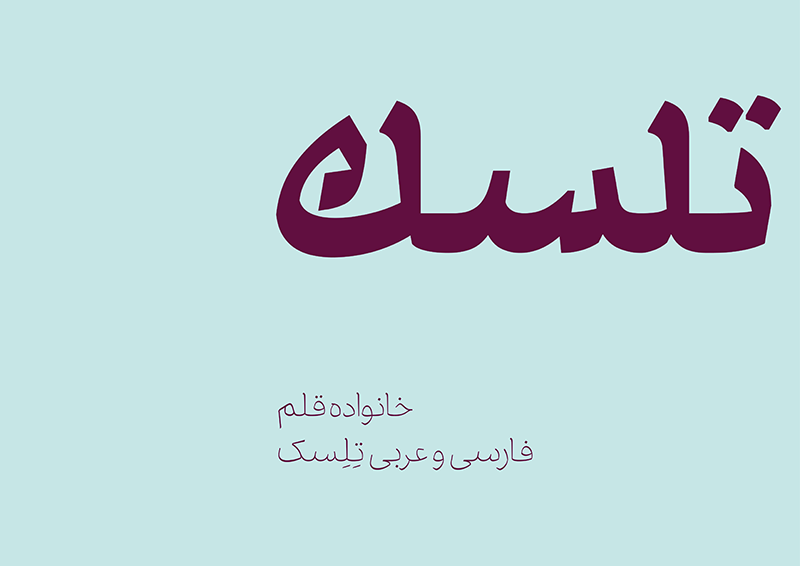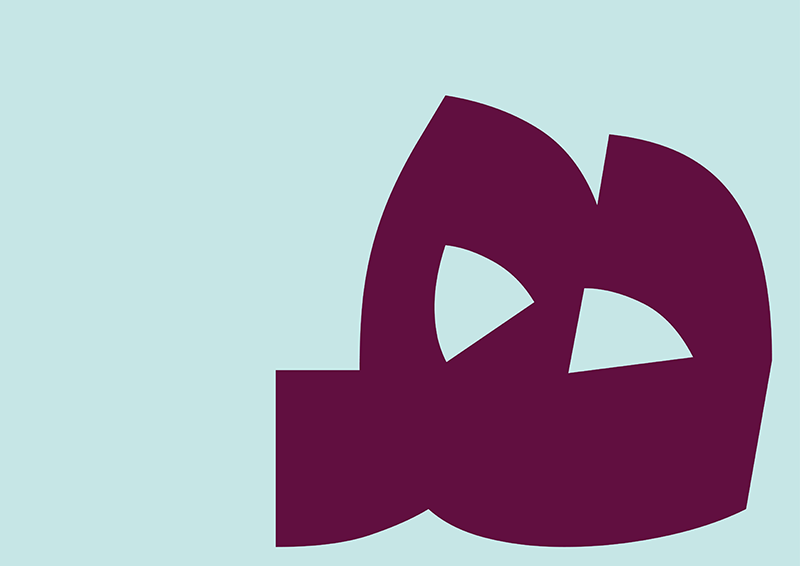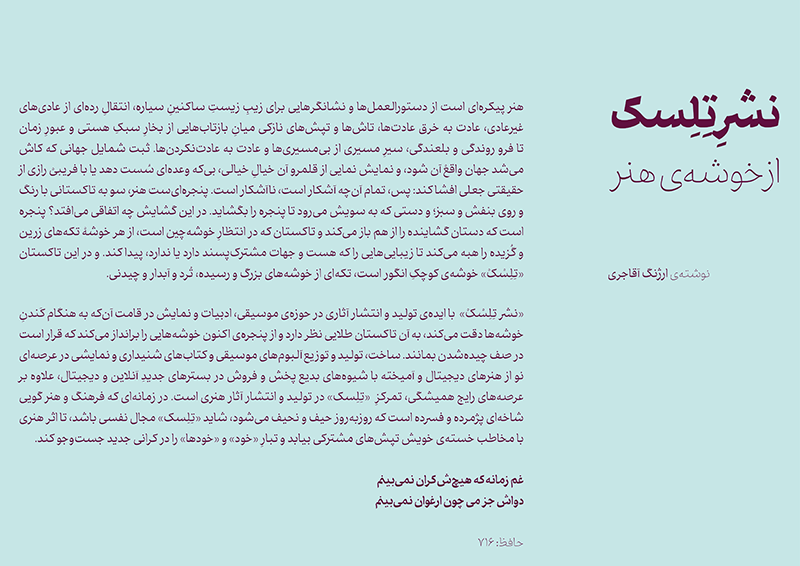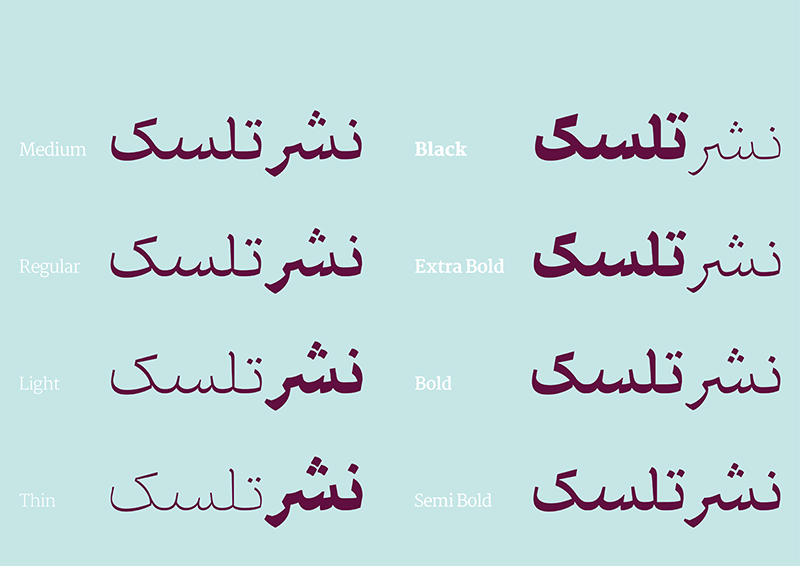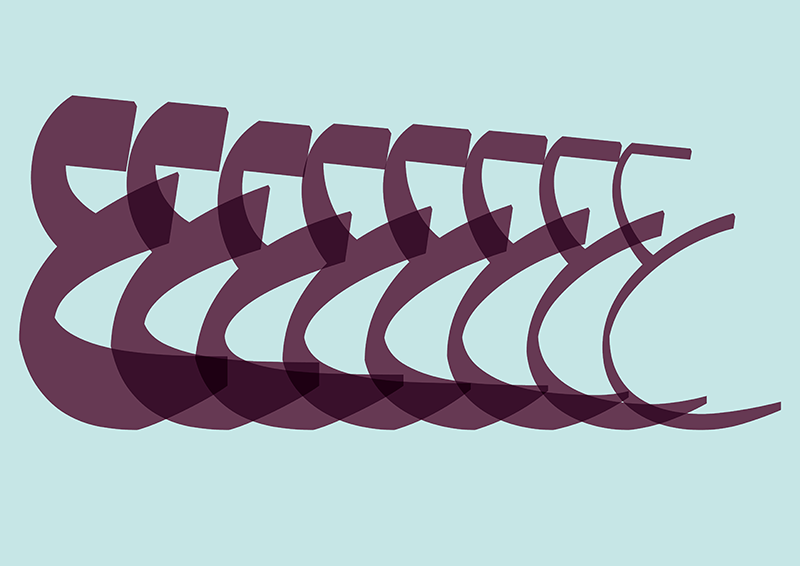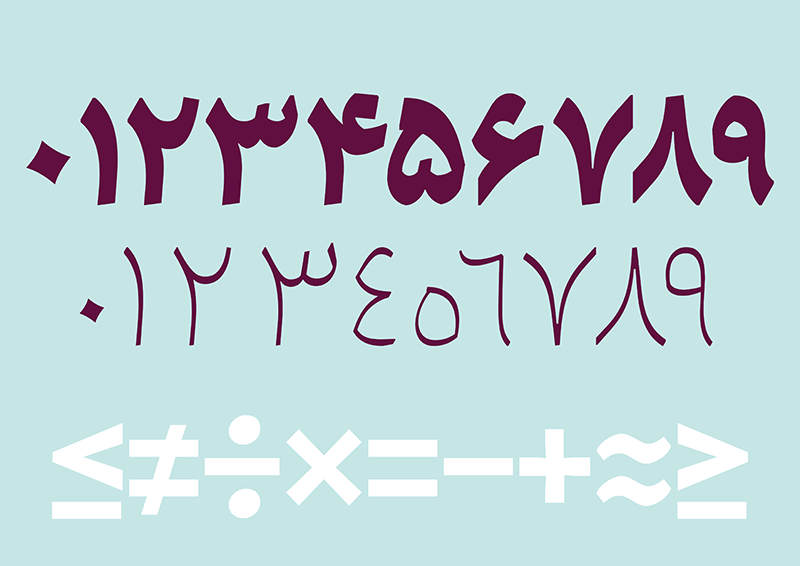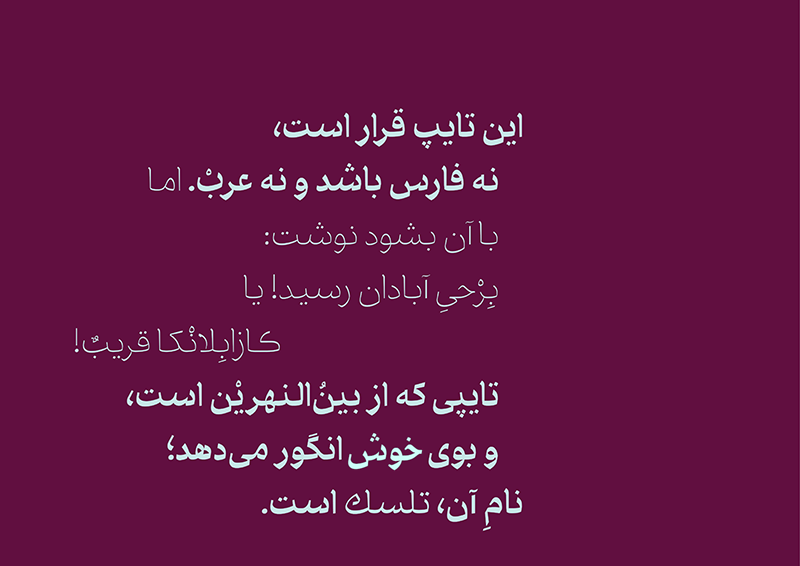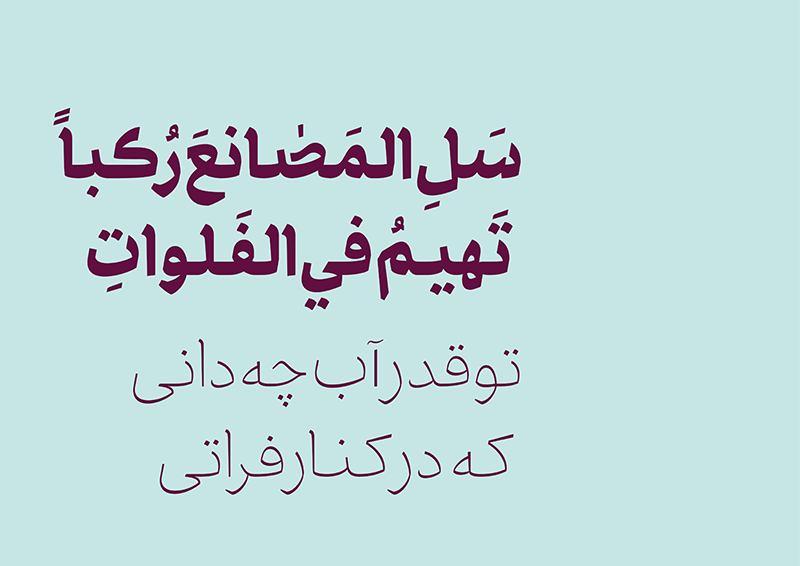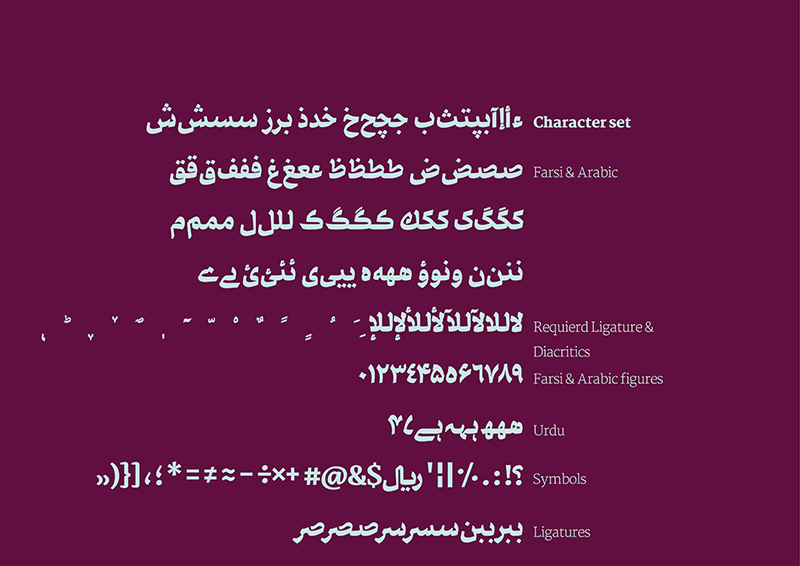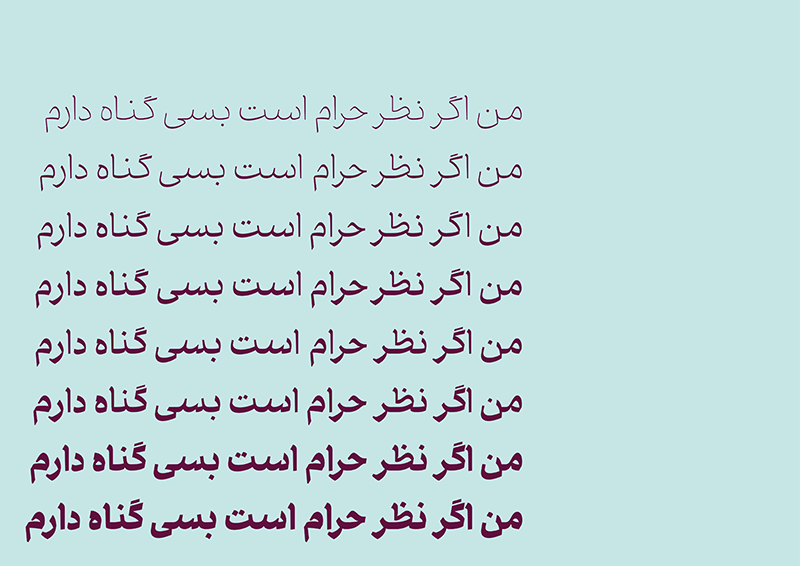
قلم تلسک font Tlesk
قلم تلسک
کاری از امیر مهدی مصلحی
درباره قلم تلسک
سال۱۳۹۶، مدیر نشر موسیقی تلسک، ارژنگ آقاجری، به استودیو مرکزی سفارش دیزاین هویت دیداری آلبوم‌های موسیقی‌اش را داد. از آنجایی که مشی دیزاین ما در استودیو مرکزی، پیروی از منطق ساده‌گرایی در دیزاین بود، بر آن شدم که با ساخت قلمی برای نوشتن عناوین آلبوم‌ها به رسیدن به راه‌حل دیزاین نزدیک‌تر شوم. بعد از شنیدن موسیقی اولین آلبوم نشر تلسک، «طاق‌های ضربی بغداد» که زخمه‌های قانون در آن چون درخشش آب‌های فرات در برق آفتاب جنوب بود، فرم‌هایی پدیدار شد که طعم و بوی آن سرزمین‌ها را داشت. افزون بر آن، موسیقی‌های نشر تلسک غالباً معاصراند؛ بنابراین ویژگی مدرن بودن در فرم‌های قلم تلسک نیز ناگزیر می‌آمد. بعد از تولید نسخه اولیه قلم تلسک به شیوه نمایشی و در وزن سیاه، در طی جلساتی با نرم‌افزاری محترم مریم، قرار بر انتشار این قلم، توسط این نهاد متخصص و باسابقه شد.
در طراحی قلم تلسک سعی شده‌است طعمی از خط رقعه، که خط مرسوم نوشتاری جهان عرب است، در آن باشد. تقطیع‌ها و شکست‌های عریان آن، به‌خصوص در حرف «س»، به تنه نخل شبیه‌است. قلم تلسک در اصل برای نوشتن عناوین تدوین شده‌بود اما به تدریج وزن‌های مناسب برای متن کتاب نیز ضروری ‌شد؛ به همین جهت خانواده قلم تلسک از چهار وزن سیاه نمایشی و چهار وزن خاکستری متن شکل گرفته‌است. متفاوت ‌بودن فرم‌ها توأم با جسارت از دیگر اهداف در دیزاین تلسک بوده‌است. ناشر محترم، ارژنگ آقاجری، در توصیف نشر تلسک اینگونه نوشته‌است:
«هنر پیکره‌ای است از دستورالعمل‌ها و نشانگر‌‌هایی برای زیبِ زیستِ ساکنینِ سیاره، انتقالِ رده‌ای از عادی‌های غیرعادی، عادت به خرق عادت‌ها، تاش‌ها و تپش‌های نازکی میانِ بازتاب‌هایی از بخارِ سبکِ هستی و عبورِ زمان تا فرو روندگی و بلعندگی، سیرِ مسیری از بی‌مسیری‌ها و عادت به عادت‌نکردن‌ها. ثبت شمایل جهانی که کاش می‌شد جهان واقعْ آن شود، و نمایش نمایی از قلمرو آن خیالِ خیالی، بی‌که وعده‌ای سُست دهد یا با فریبیْ رازی از حقیقتی جعلی افشا کند: پس، تمام آن‌چه آشکار است، ناآشکار است. پنجره‌ای‌‌ست هنر، سو به تاکستانی با رنگ‌ و روی بنفش‌ و سبز؛ و دستی که به سویش می‌رود تا پنجره را بگشاید. در این گشایش چه اتفاقی می‌افتد؟ پنجره است که دستان گشاینده را از هم باز می‌کند و تاکستان که در انتظارِ خوشه‌چین است، از هر خوشهْ تکه‌‌های زرین و گُزیده را هبه می‌کند تا زیبایی‌هایی را که هست و جهات مشترک‌پسند دارد یا ندارد، پیدا کند. و در این تاکستان «تِلِسْکْ» خوشه‌ی کوچکِ انگور است، تکه‌ای از خوشه‌ها‌ی بزرگ و رسیده، تُرد و آبدار و چیدنی.»
امیر مهدی مصلحی
امیرمهدی مصلحی، متولد ۱۳۶۸، طراح حروف، خوشنویس و پژوهشگر ایرانی است که در آلمان سکونت دارد. او دانش‌آموختهٔ کارشناسی معماری از دانشکدهٔ هنرهای زیبای دانشگاه تهران است و تحصیلاتِ خود در طراحیِ حروف را در کشور فرانسه، مرکز ملی تحقیقات تایپوگرافیک* در دورهٔ پست‌مستر مدرسهٔ ملی هنر و دیزاین نانسی تکمیل کرده و پس از آن مشغولِ تحصیل در مقطع کارشناسی ارشدِ مطالعاتِ فرهنگ‌های مصنوعات نوشتاری و نسخ خطی در دانشگاه هامبورگ** شده است. کارهای طراحی حروف او محصول پژوهش‌های عمیق در نسخ خطی و آثارِ خوشنویسی است. برخی از قلم‌های او در ایران توسط نرم‌افزاری مریم منتشر شده است. در سال‌‌های اخیر نیز سابقهٔ همکاری با شرکت‌های مطرحِ جهانی طراحی حروف، نظیر Typotheque، TPTQ Arabic، Rosetta و دیگر مجموعه‌ها داشته است.
*Atelier National de Recherche Typographique
** Centre for the Study of Manuscript Cultures